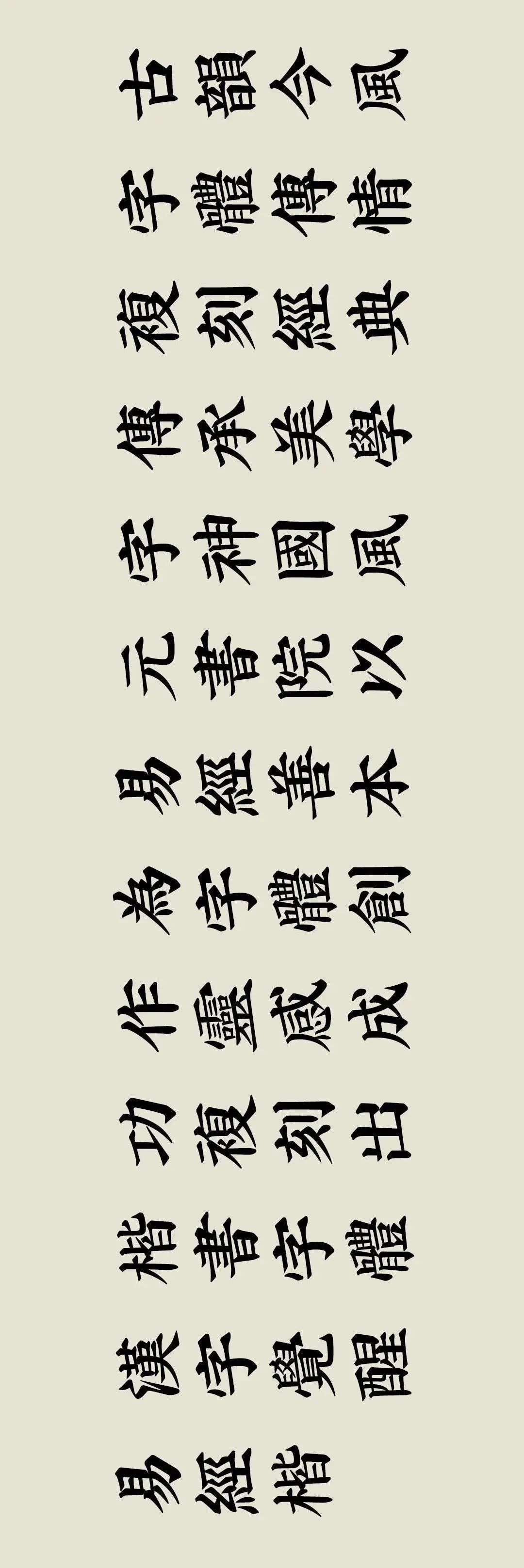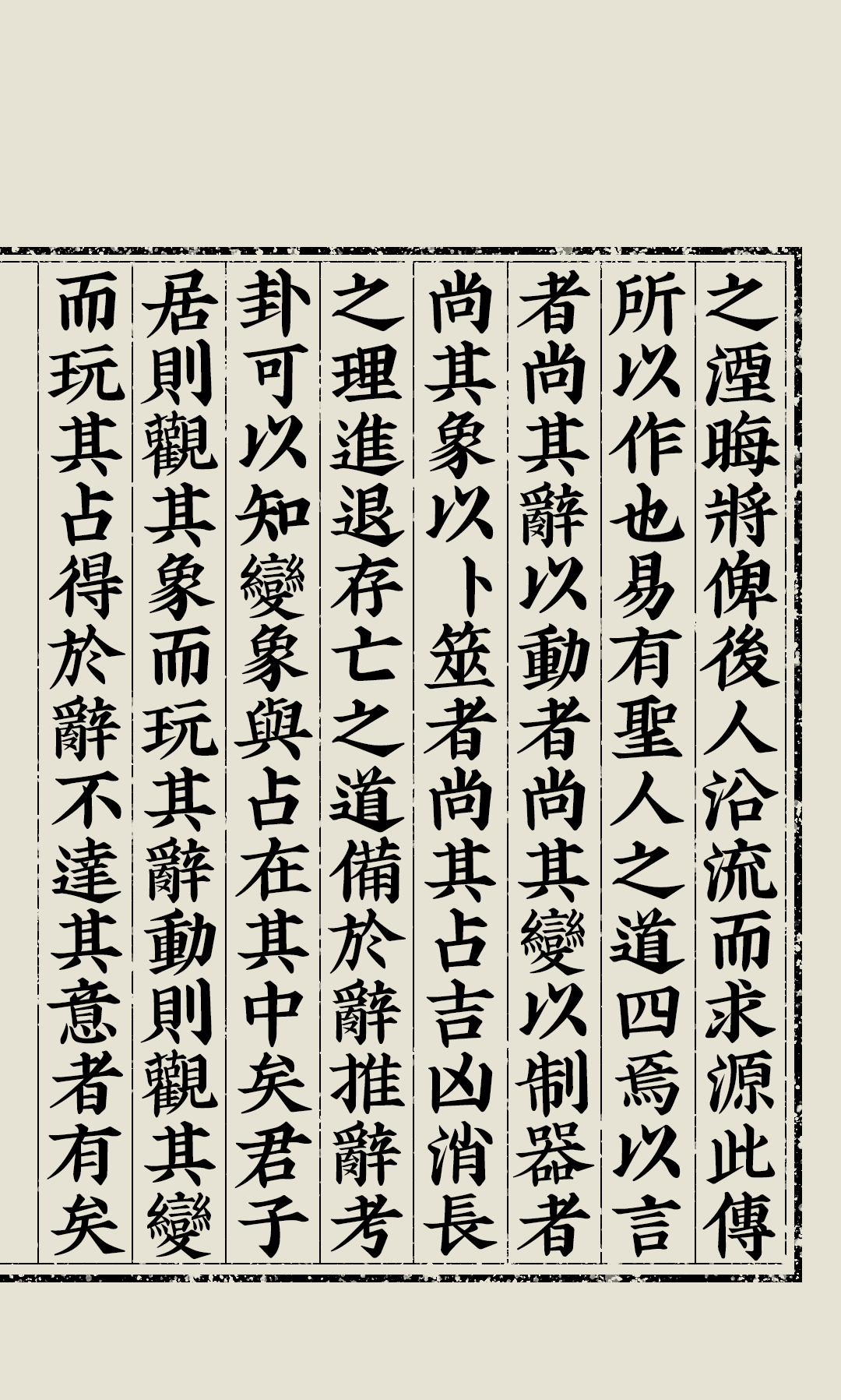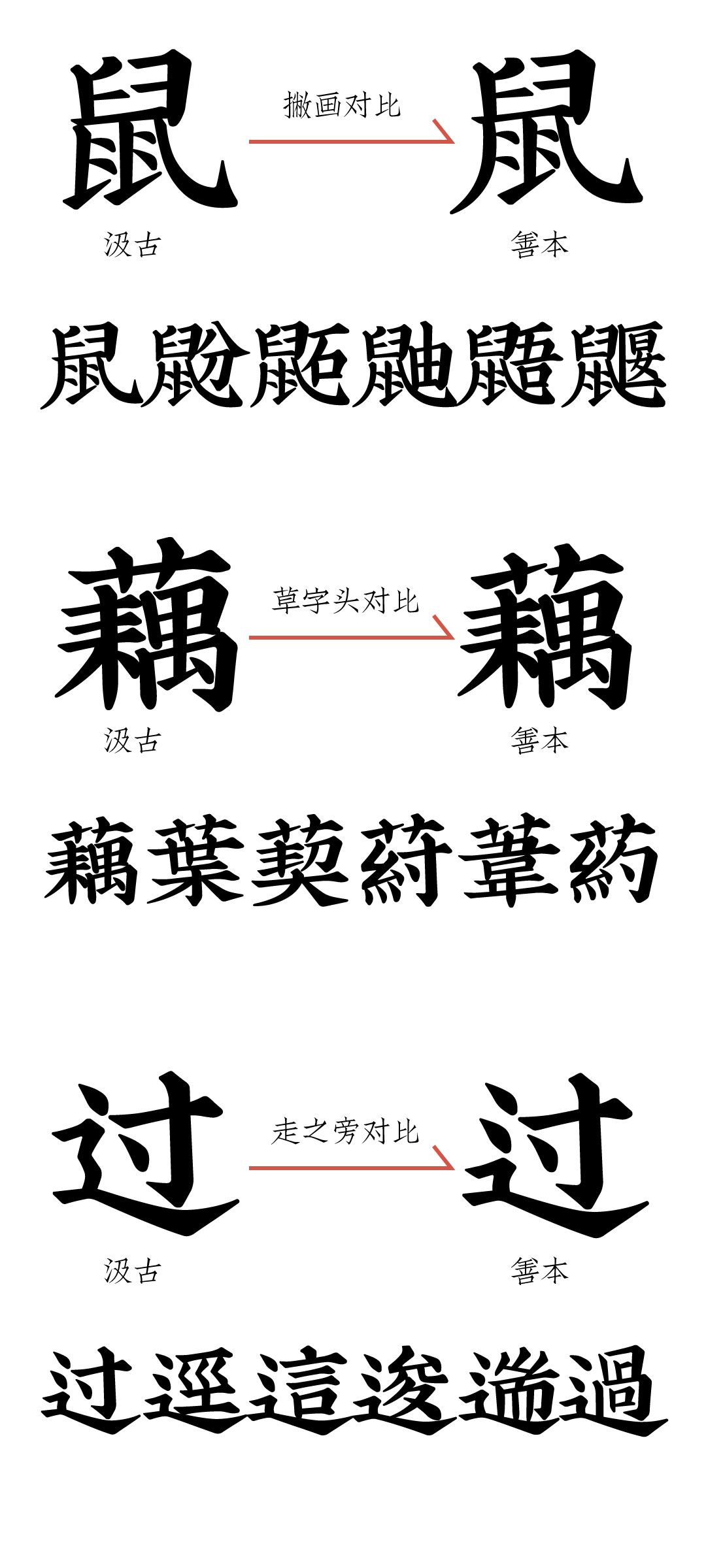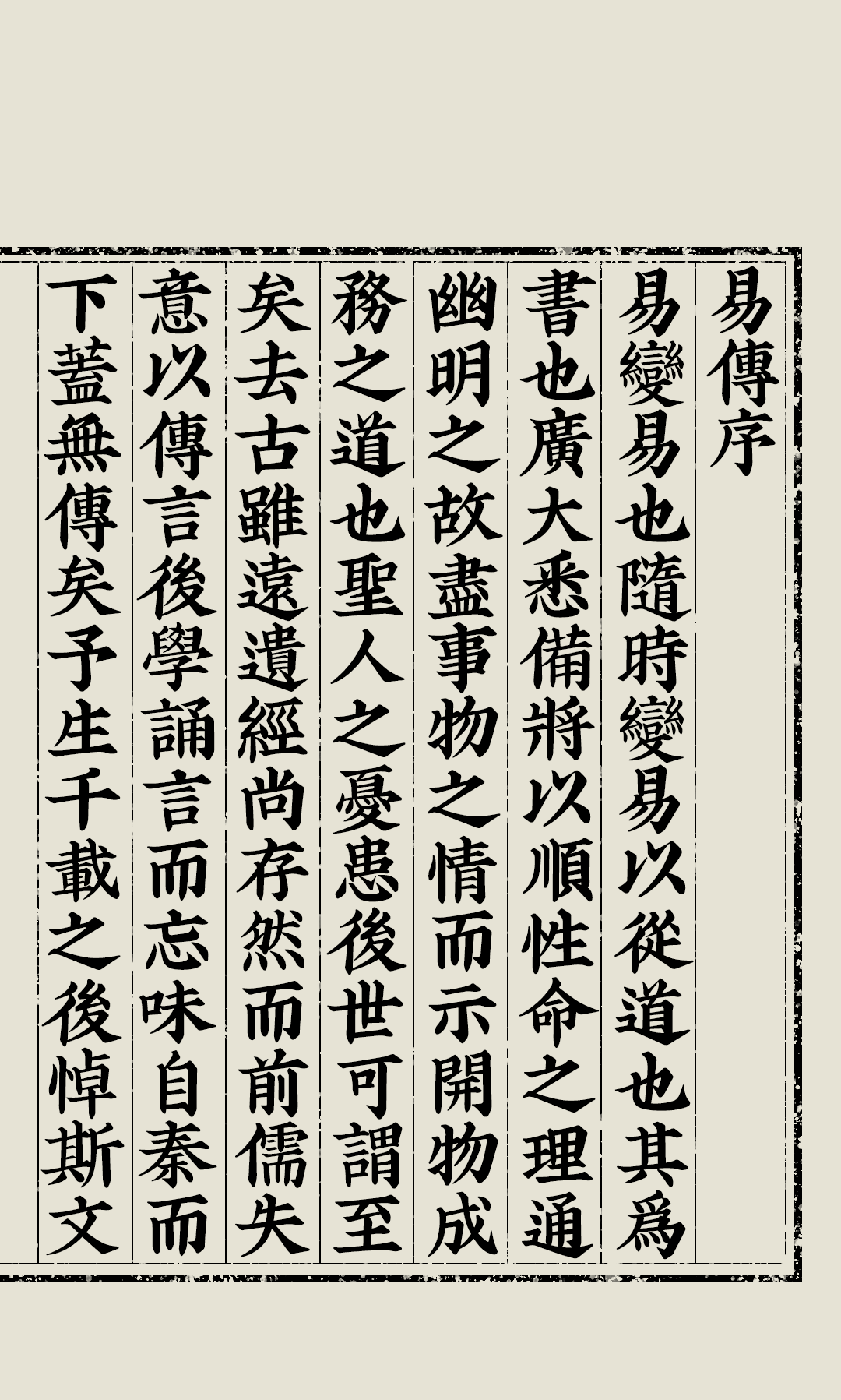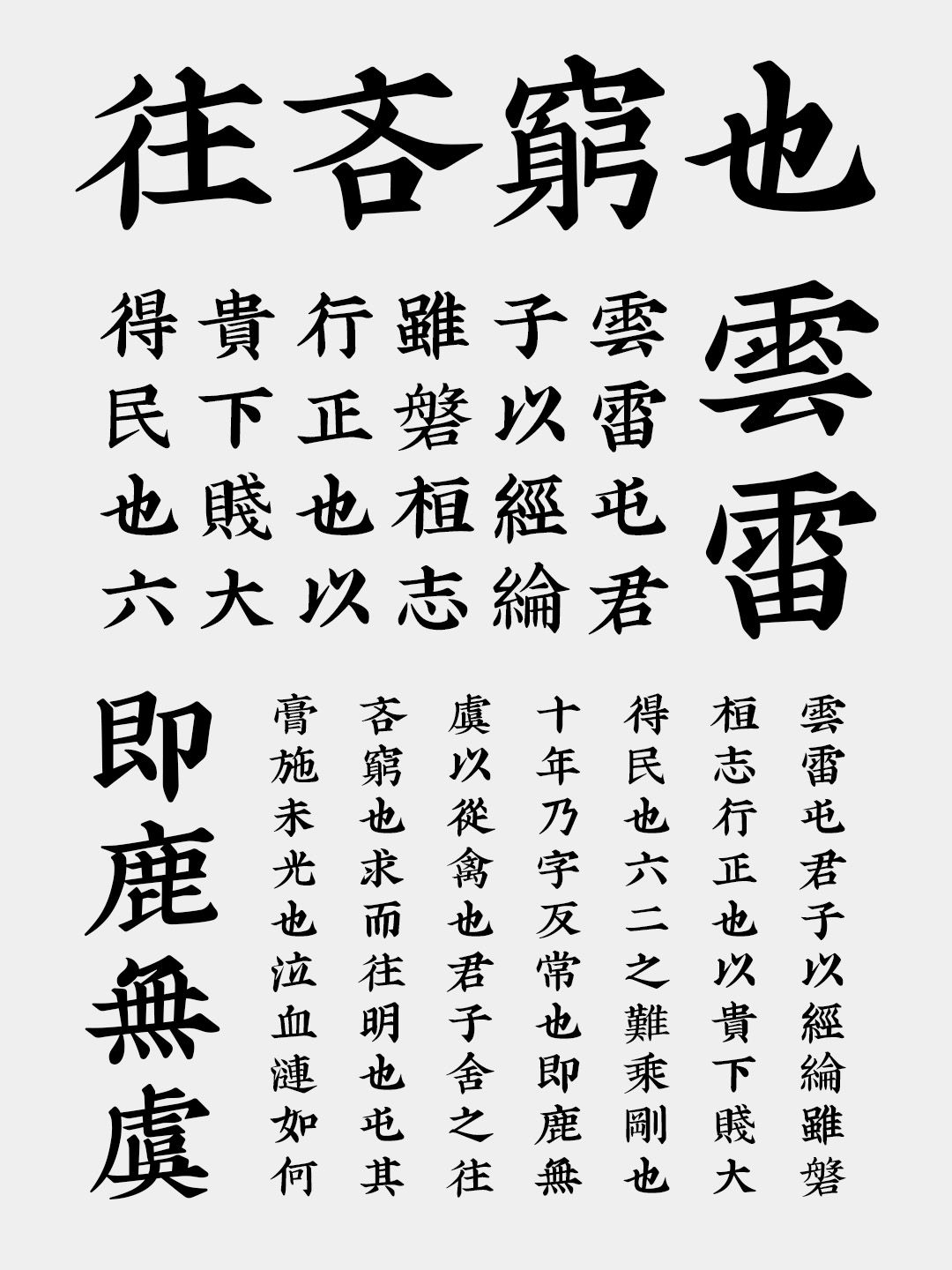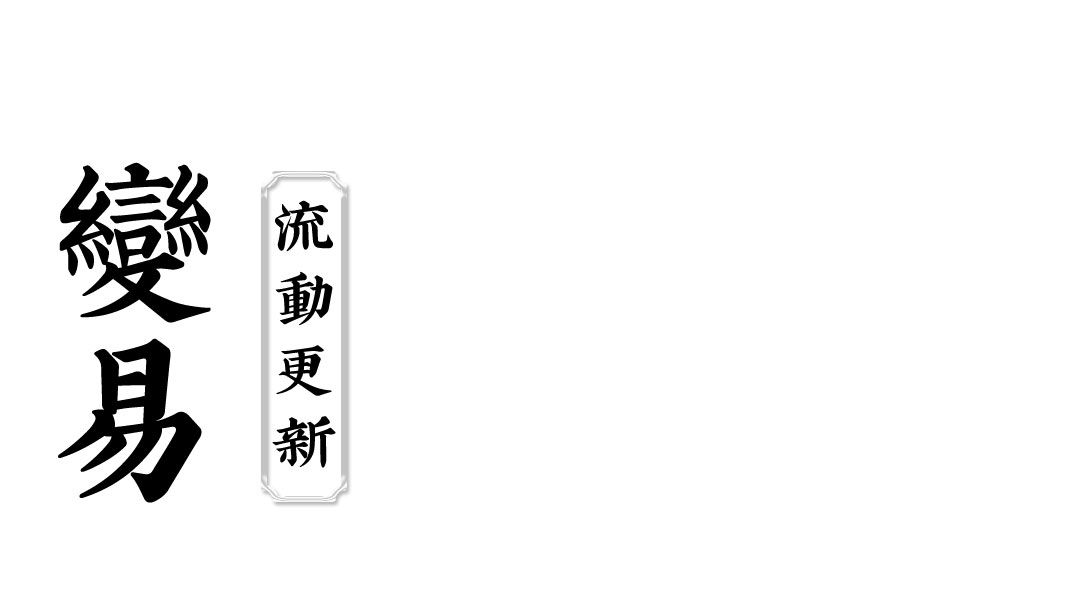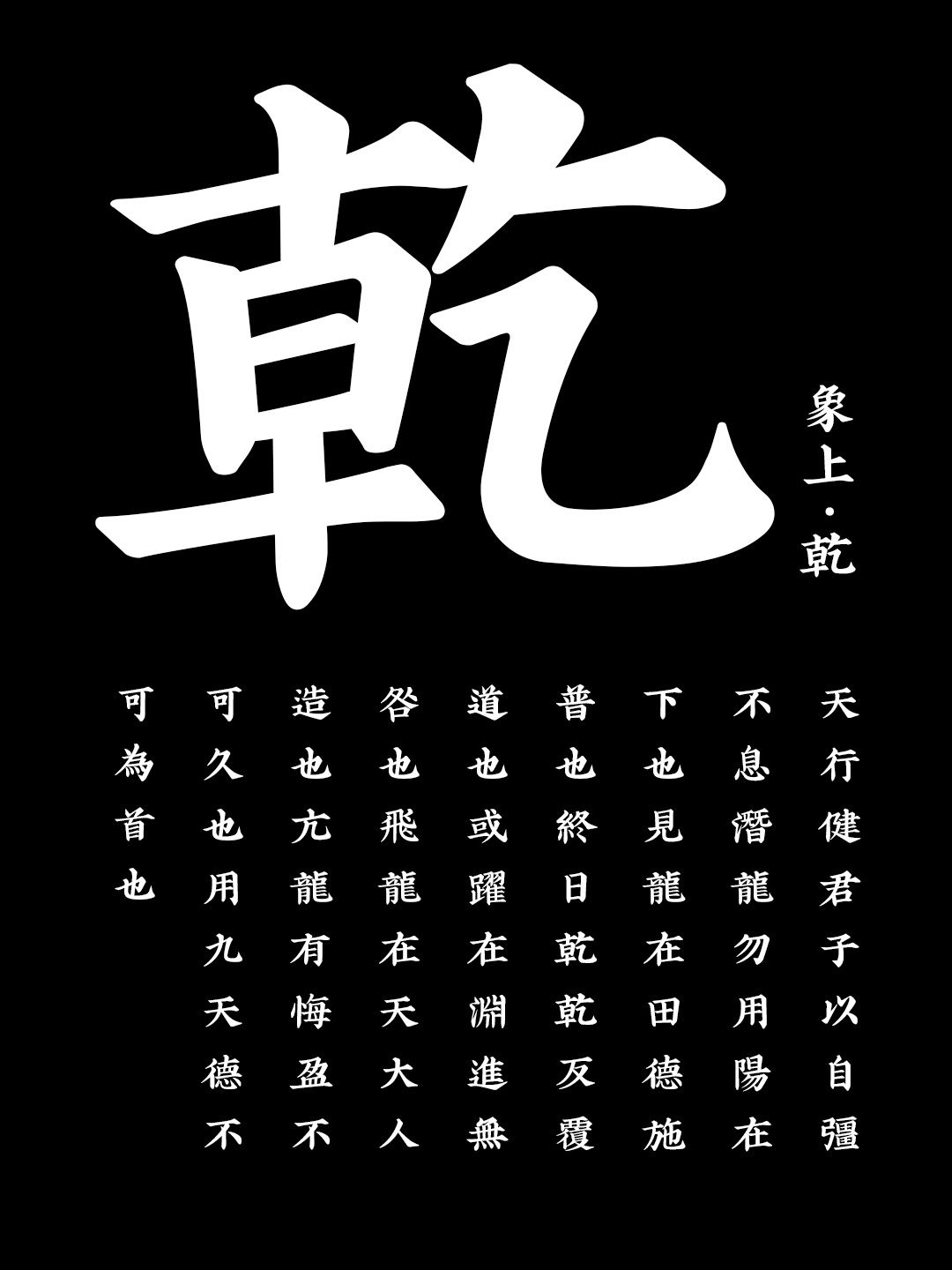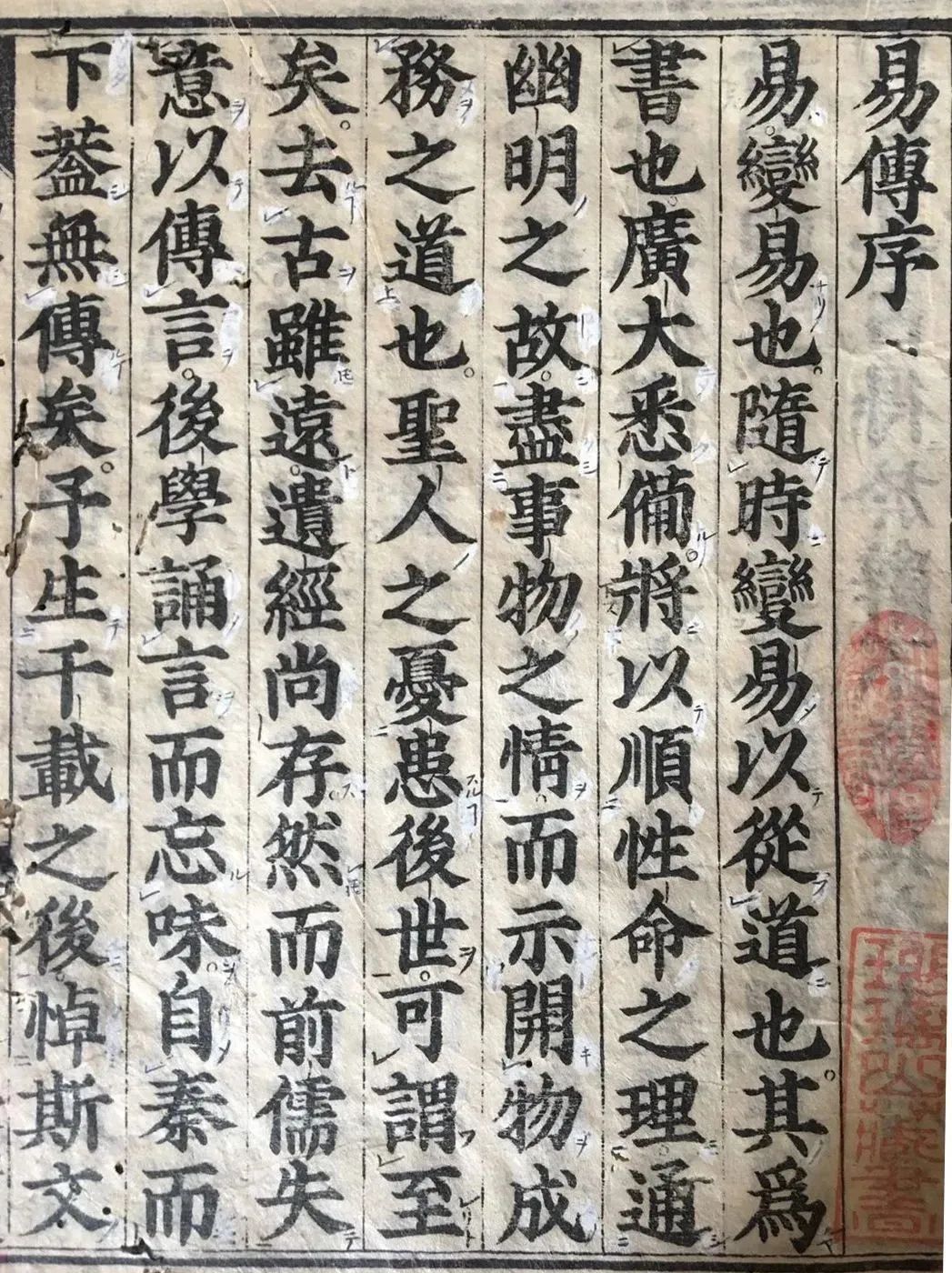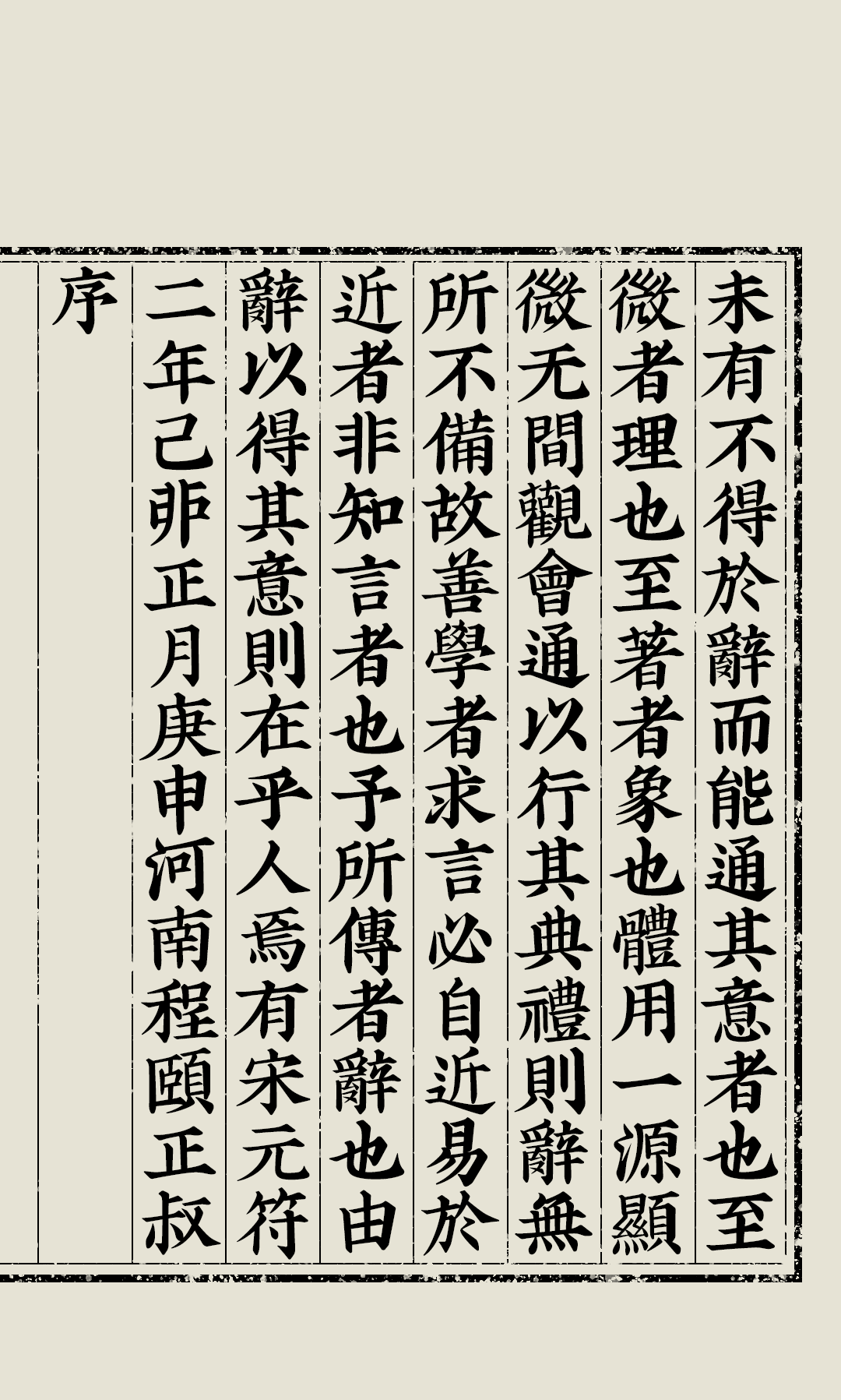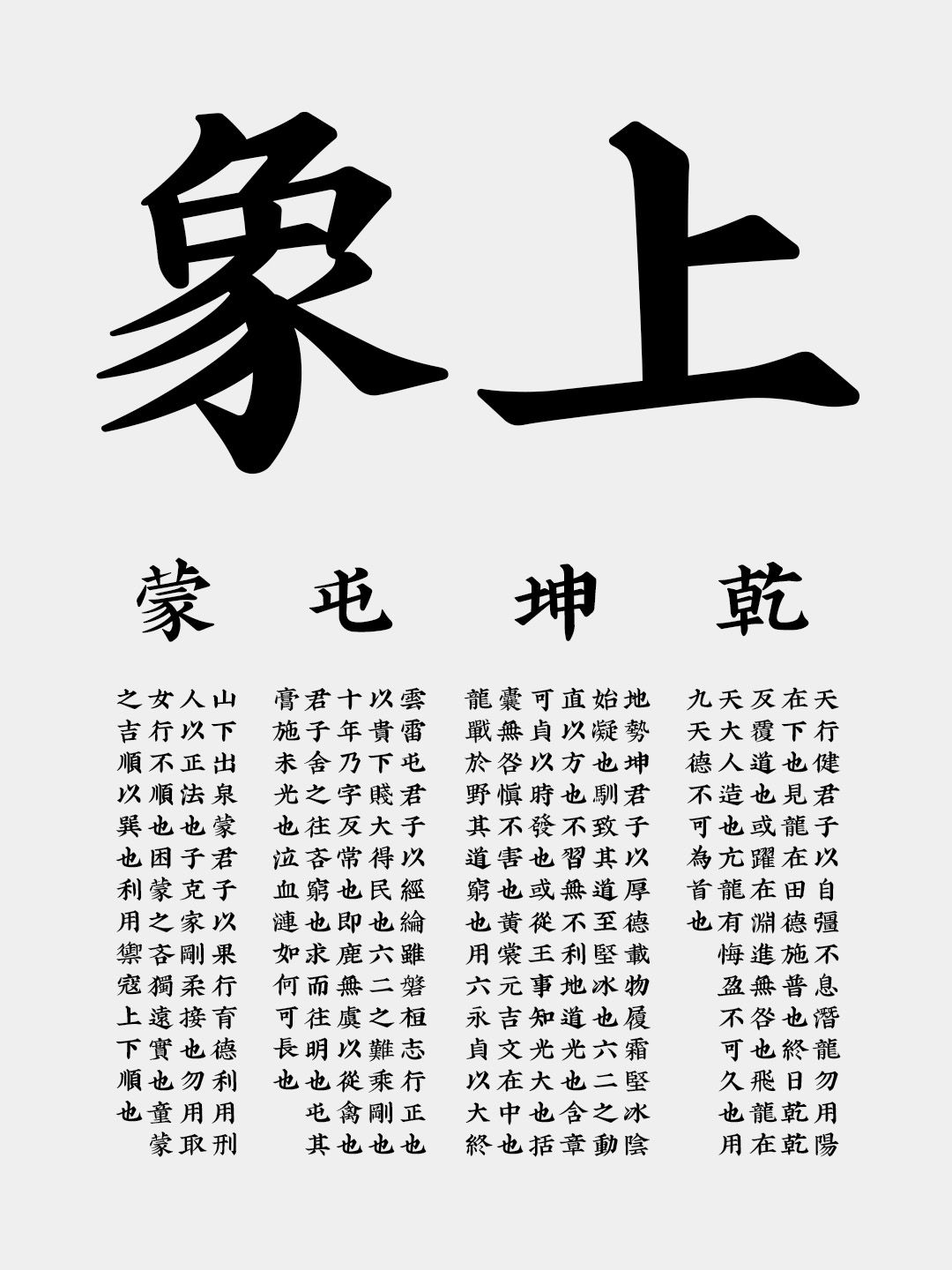
中国风善本之美,易经觉醒之美,我太爱了!
汉字觉醒
中国藏书浩如烟海,其中,善本是具有极高的文献价值、版本价值、艺术价值、学术价值和文物价值的珍贵文化遗产。在现代,善本的定义更加广泛,只要刻印较早、流传较少的各类古籍都被认为是善本。
《易经》作为阐述天地世间万象变化的古老经典,其留存于世的善本资料,对于研究中国传统文化不可或缺。它以宏大而辽阔的视野,揭示藏在宇宙中的秘密,道明人生发展的规律,以“字”的形式流传,指引世人,成为东方美学的生动注脚。
中华善本数字化是保护和传承中华文明的一种重要方式。通过将《易经》善本字体进行字库制作,我们可以与千年文化直接对话,让更多现代人接触并了解千载传承的中华文明。
字神国风元书院,以古籍善本《易经》的原版字体为基础字形,设计出一款复刻字体——汉字觉醒易经楷 善本/汲古,流淌着古人的智慧与简朴,致力于研究古籍字在现代排版中的应用拓展,展示汉字之美,同时让现代读者能够更好地阅读和理解古代文献,助力善本保护事业。
善本对于现代字体设计与发展具有重要价值与启发,从善本中汲取灵感,开发出具有中华传统文化特色的新字体,为现代字体设计注入新的活力,是字库行业未来的重要方向。
汉字觉醒易经楷 善本/汲古,是一次“汉字觉醒”的重要尝试,也是传承“东方美学”的字库实践,为现代排版及应用提供更多字体选择,适合应用于标题、正文排版、LOGO等场景。